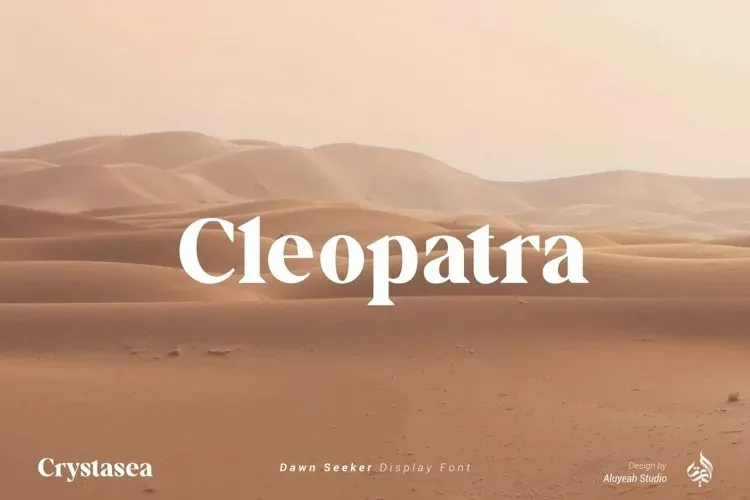
A Crystasea Font é uma elegante serif moderna criada pela Aluyeah Studio com quatro estilos de peso distintos e estilo espetacular. Seu design contínuo e detalhado são perfeitos para uso em materiais que exigem um toque elegante e sofisticado, como editoriais de jornais ou anúncios de alta qualidade. Esta fonte é uma ótima escolha para quem busca uma opção moderna e sofisticada para seus projetos gráficos, sem comprometer a delicadeza do estilo serif clássico. Com seu design minimalista e harmonioso, a Crystasea Font pode ser usada em diversos ambientes de design, desde editoriais até websites, oferecendo uma alternativa versátil ao tradicional tipo serif. Eles são perfeitos para dar um toque sofisticado aos seus projetos digitais ou impressos sem comprometer o equilíbrio visual de seu layout.